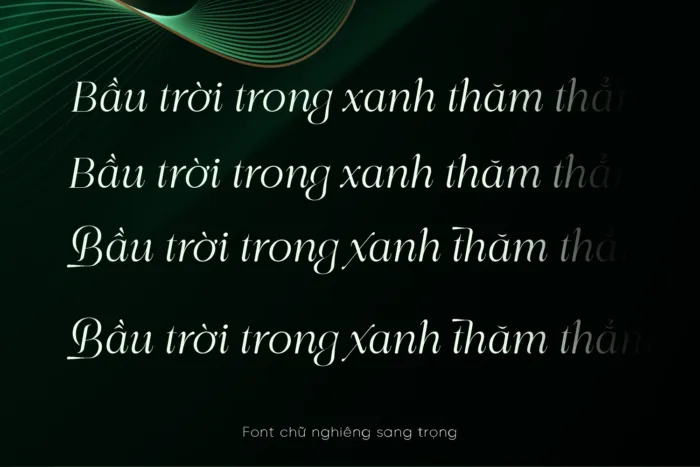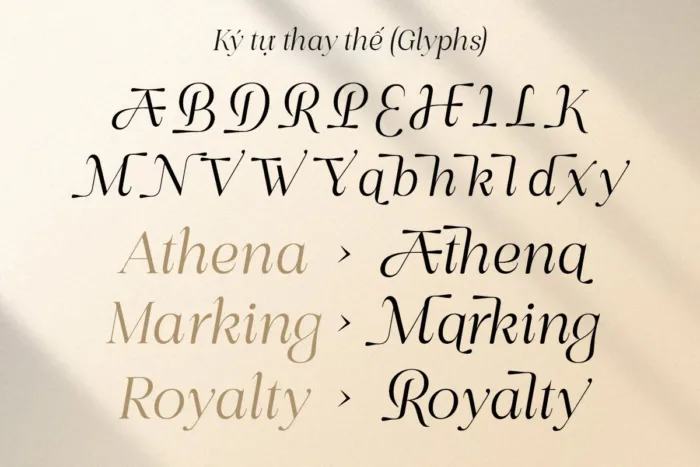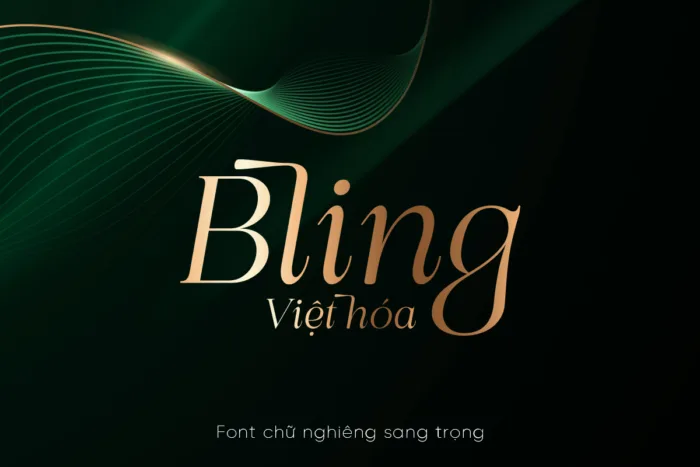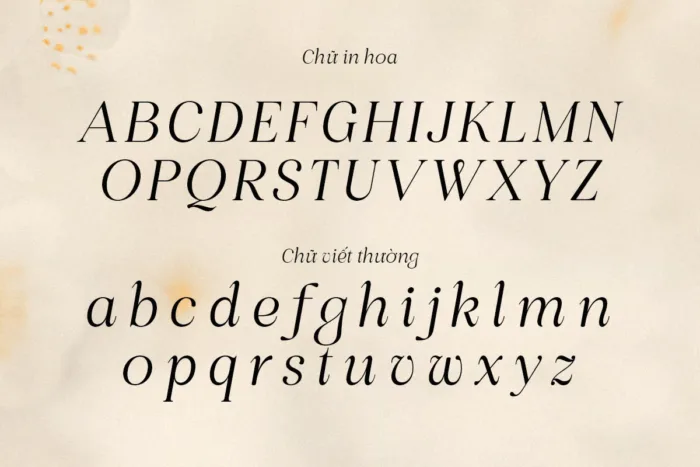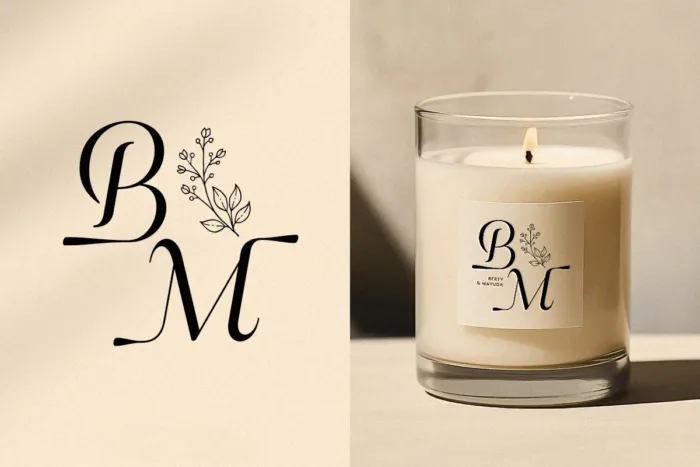
DVN Bling Việt hóa – Font chữ Serif nét nghiêng sang trọng và quý phái
DVN Bling là font chữ serif hiện đại được thiết kế tinh tế dành riêng cho các thương hiệu đẳng cấp trong lĩnh vực thời trang, mỹ phẩm, trang sức và đồ cao cấp. Với những nét thanh mảnh, độ tương phản nhẹ nhàng và các chi tiết bo góc tinh xảo, font chữ mang đến vẻ sang trọng đầy tinh tế.
Được Việt hóa hoàn chỉnh với đầy đủ dấu tiếng Việt, DVN Bling đặc biệt phù hợp cho:
• Logo thương hiệu cao cấp
• Bao bì sản phẩm mỹ phẩm, nước hoa
• Ấn phẩm thời trang sang trọng
• Thiết kế minimalist nhưng đầy đẳng cấp
Với nhiều độ đậm nhạt linh hoạt, font chữ giúp thể hiện sự quý phái mà không kém phần hiện đại, trở thành lựa chọn hoàn hảo cho những thương hiệu muốn khẳng định đẳng cấp.